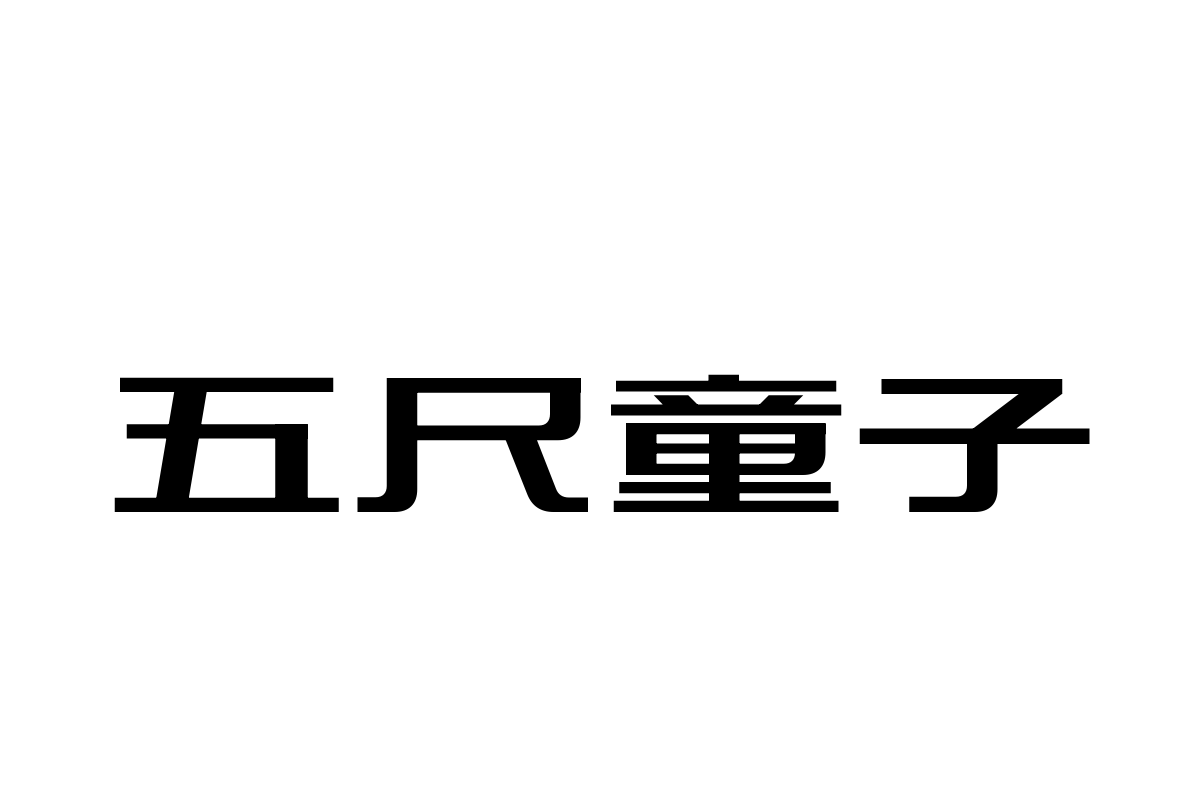
三极刃黑粗字体是一种具有显著特点的汉字字体。这种字体的特点是笔画粗细不一,给人一种强烈的视觉冲击。它的设计灵感来源于传统的书法艺术,通过独特的笔画结构和粗细变化,展现出汉字的独特韵味和美感。
三极刃黑粗字体的特点在于其笔画的粗细变化。在书写过程中,每个字的笔画都会根据需要调整粗细,以表现出不同的情感和意境。这种设计使得字体更加富有表现力,能够更好地传达作者的思想和情感。
此外,三极刃黑粗字体还具有一定的艺术性。它的笔画结构复杂而精致,线条流畅而有力,给人一种优雅而庄重的感觉。这种字体不仅适合用于正式场合的书写,也非常适合作为艺术品展示。
总之,三极刃黑粗字体是一种独特而富有表现力的汉字字体,它以其独特的笔画粗细变化和艺术性特点,为人们提供了一种全新的书写体验。